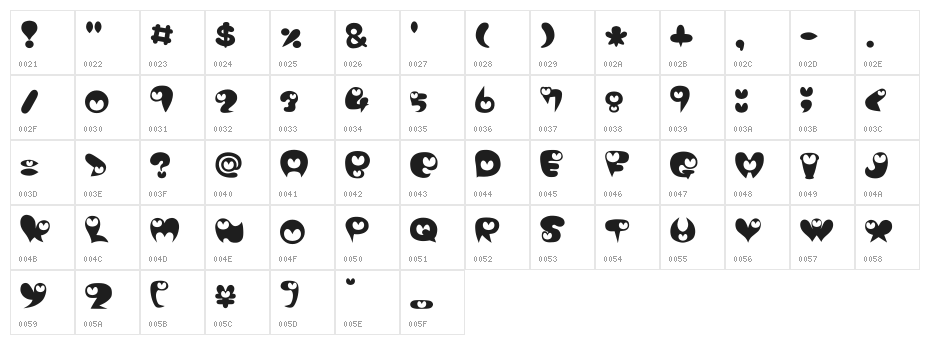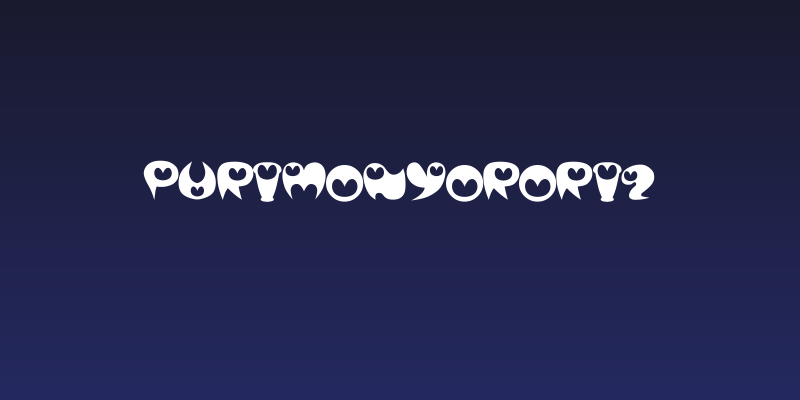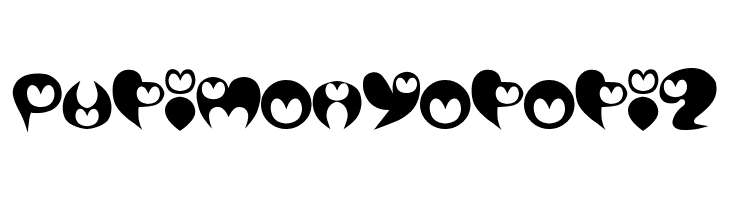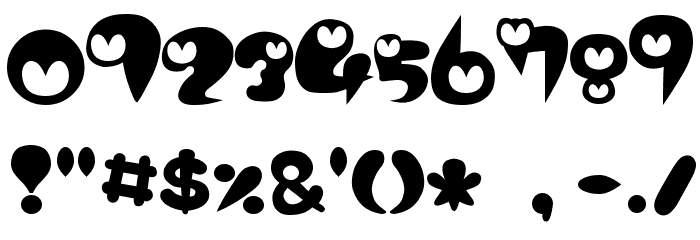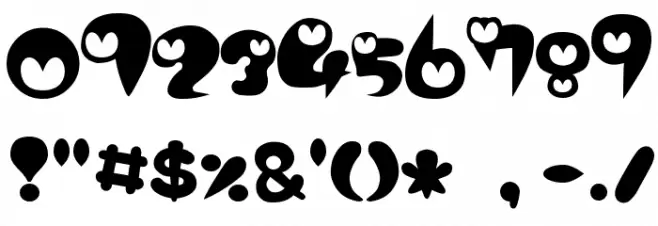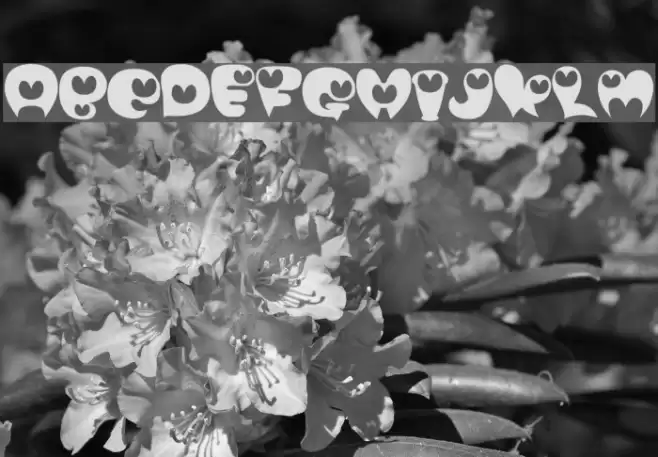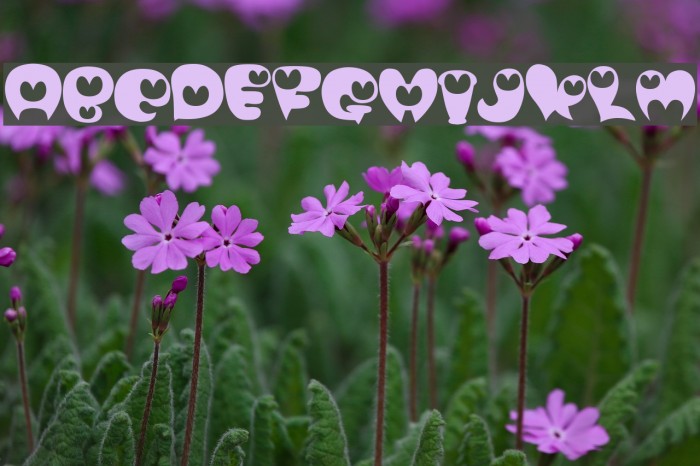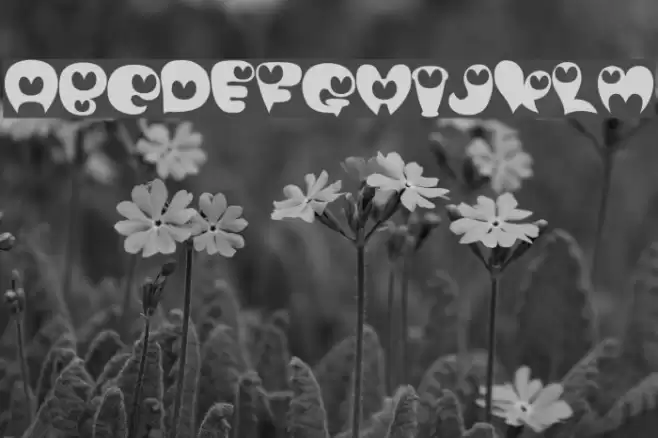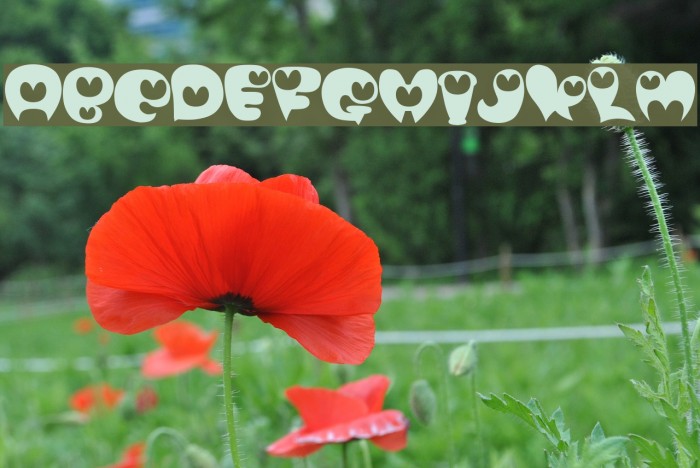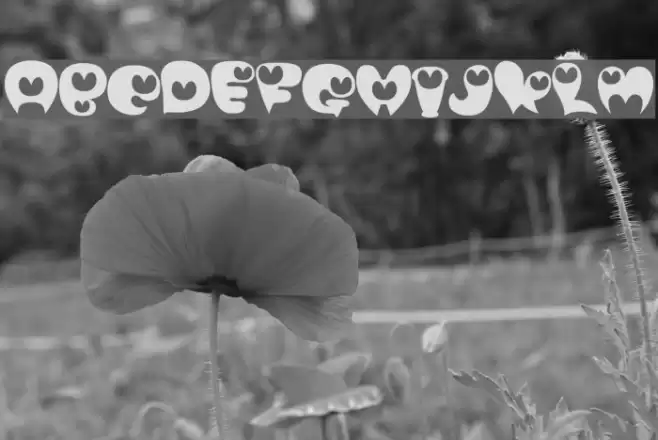
purimonyorori2 Font
| Stile generale | Playful, Whimsical |
| Caso d'uso | Logos, Headlines, Invitations |
| Progetti proposti | Perfect for Valentine's Day cards, children's books, playful branding, and love-themed event invitations. |